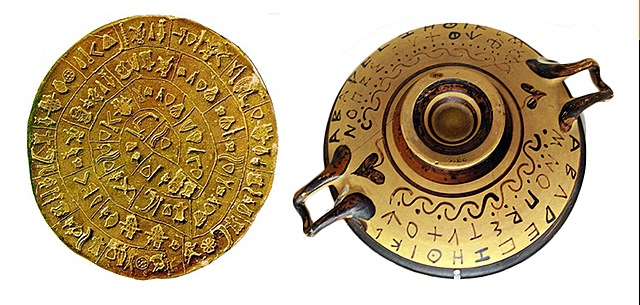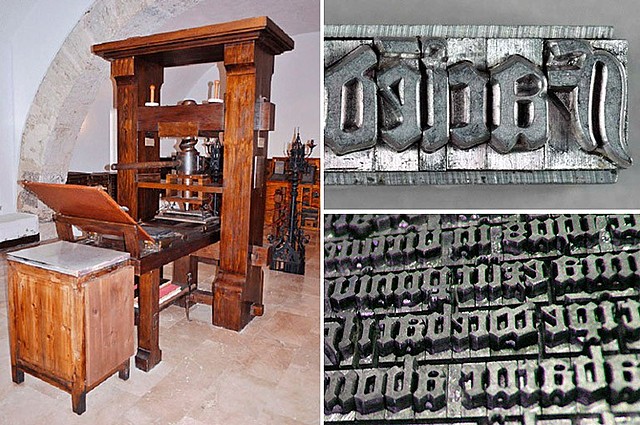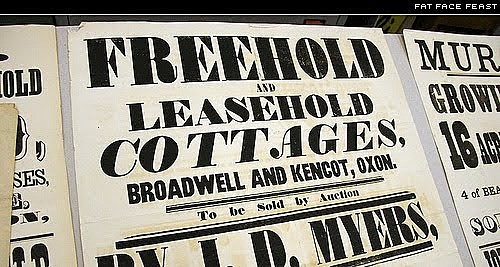
La escritura pictográfica o simplemente pictografía es una forma de comunicación escrita que se remonta al neolítico, donde el hombre usaba las pictografías para representar objetos mediante dibujos en una lámina de piedra.
Los jeroglíficos fueron un sistema de escritura inventado por los antiguos egipcios. Fue utilizado desde la época pre-dinástica hasta el siglo IV. Los antiguos egipcios usaron tres tipos básicos de escritura: jeroglífica, hierática y demótica; esta última corresponde al Periodo tardío de Egipto
Su soporte son tabletas de arcilla y ocasionalmente tabletas de metal y piedra, y su origen está en la antigua Mesopotamia. Se llama cuneiforme porque para trasladarla a la arcilla húmeda utilizaban unas cañas biseladas en forma de cuña.
El jeroglífico cretense es un sistema de escritura silábico que se utilizó en Creta en época minoica. Todavía no ha sido descifrado. Su corpus lo forman unos 350 documentos que contienen un total de aproximadamente 3000 signos.
Se le denomina semítico septentrional y aparece como una combinación de los símbolos cuneiformes y jeroglíficos; algunos signos podrían proceder de otros sistemas emparentados con ellos como la escritura cretense e hitita. El alfabeto semítico sólo tenía 22 consonantes.
Los fundidores de letras londinenses lograron diseños innovadores.
William Calson fue el abuelo de esta revolución. Además de sus herederos, dos de sus anteriores aprendices Joseph Jackson (1733-1792) y Thomas Cotterell (muerto en 1785), llegaron a ser prósperos diseñadores de letras y fundidores.
Aparentemente Cotterell inició la tendencia a fundir, en moldes de arena, toscas letras negritas, a principios del año 1765. -
Su invención se debe a pierre de la ramme. Contemporáneo de Erasmo de Rotterdam, quien propuso utilizar dos nuevos signos alfabéticos para representar dos fonemas que ya para entonces eran distintos. Pero la diferenciación que en principio era ocasional no se convertiría en una norma hasta el siglo XVIII, momento en que quedan establecidas las 26 letras del alfabeto latino básico tal como las conocemos actualmente.
La imprenta es un método mecánico destinado a reproducir textos e imágenes sobre papel, tela u otros materiales. En su forma clásica, consiste en aplicar una tinta, generalmente oleosa, sobre unas piezas metálicas para transferirla al papel por presión.
El alfabeto griego es un alfabeto de veinticuatro letras utilizado para escribir la lengua griega. Desarrollado alrededor del siglo IX a.
El alfabeto arameo es un alfabeto abyad diseñado para escribir idioma arameo. Como los otros abyads, todas las letras representan consonantes; algunas matres lectionis son consonantes que también representan vocales largas. Las inscripciones más tempranas en el idioma arameo usan el alfabeto fenicio.
Un manuscrito ilustrado o manuscrito iluminado es un manuscrito en el que el texto es complementado con la adición de decoración, tal como letras capitales decoradas, bordes y miniaturas. En la definición más estricta del término, un manuscrito ilustrado es únicamente aquel que ha sido decorado con oro o plata.
El alfabeto latino, abecedario latino, alfabeto romano o abecedario romano es el sistema de escritura alfabético más usado del mundo hoy en día, con más de 2500 millones de personas. Se compone de 27 letras principales, más ciertas modificaciones y letras adicionales según el idioma del que se trate.
Apple Macintosh permite que la tipografía llegue a millones de usuarios
Al principio un medio poco interactivo, las páginas web copian el aspecto de los documentos de papel
La web 2.0 se vuelve más interactiva, con diseños líquidos donde el usuario elige diferentes configuraciones, la cantidad de estímulos aumenta y nuestra atención se disgrega por la cantidad de contenidos que nos ofrecen.